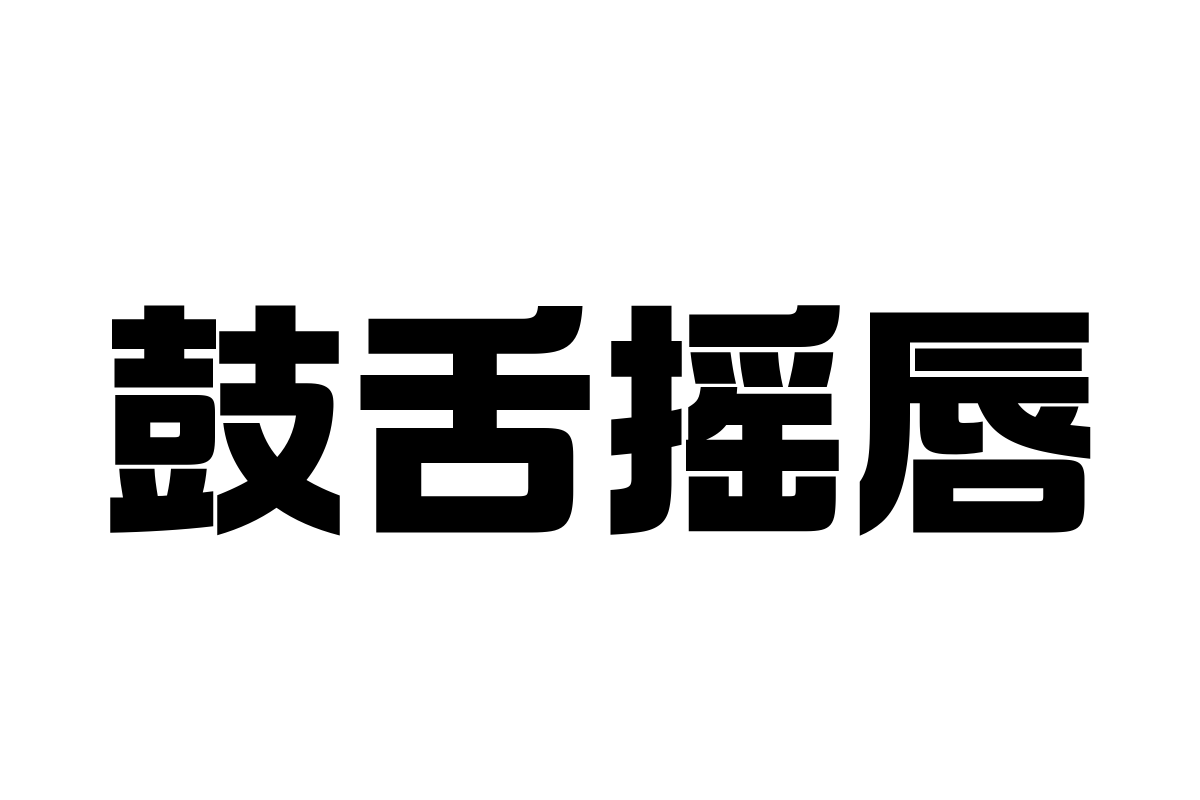
汉仪风尚黑95w是一款具有现代感的无衬线字体,它以其简洁、清晰的线条和优雅的书写风格而闻名。这款字体适用于各种设计项目,如广告牌、标志、包装、网站和其他品牌材料。
汉仪风尚黑95w的特点包括:
1. 简洁的线条:该字体采用了流畅的直线,没有过多的装饰性细节,这使得它在视觉上更加简洁明了。
2. 优雅的书写风格:字体的笔画呈现出一种优雅的书写风格,适合用于需要传达专业和正式感觉的设计。
3. 可读性强:由于其简洁的线条和清晰的结构,汉仪风尚黑95w在各种背景和尺寸下都具有很高的可读性。
4. 多种字重选择:除了基础的95号字重外,汉仪风尚黑95w还提供了其他几种不同的字重,以满足不同设计需求。
总之,汉仪风尚黑95w是一款功能强大且易于使用的无衬线字体,适用于各种需要清晰、专业设计的场景。